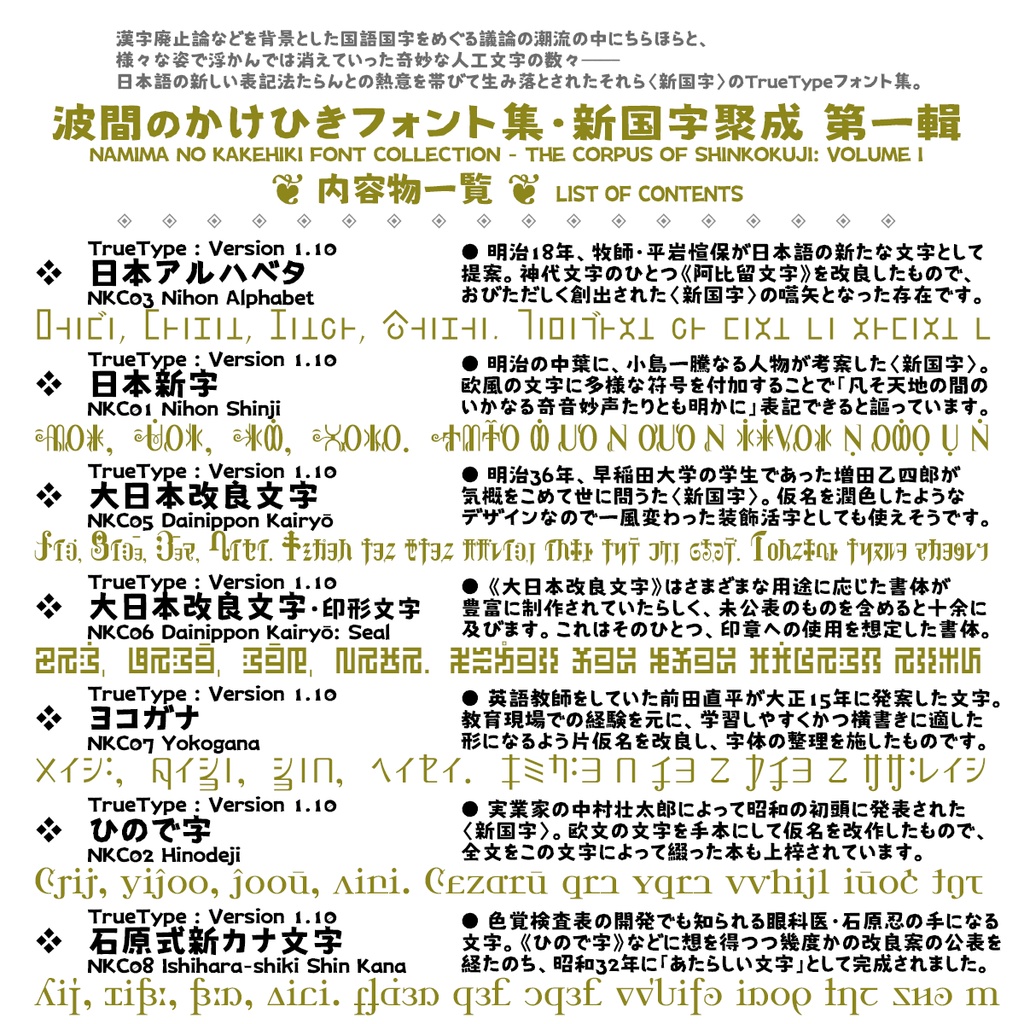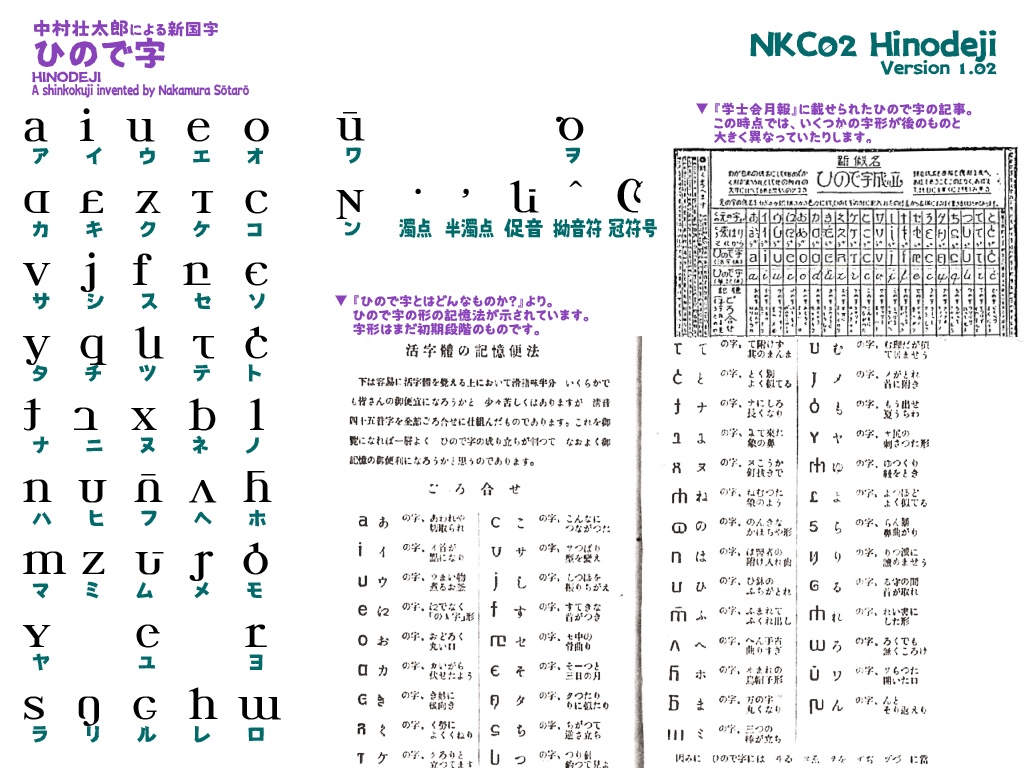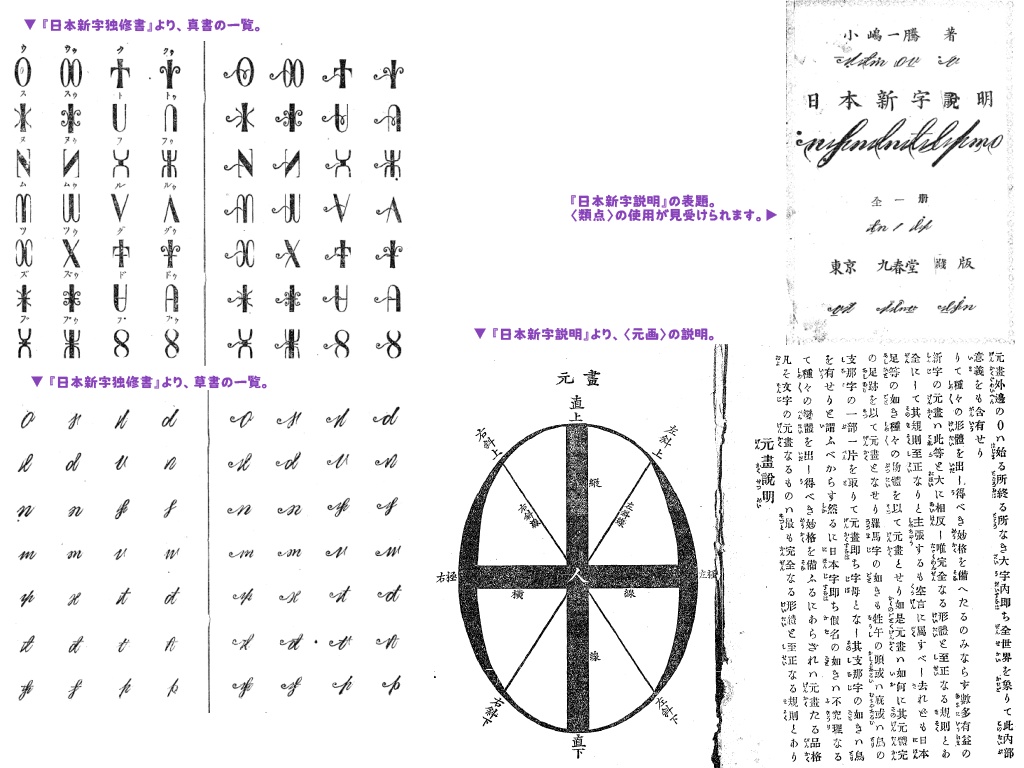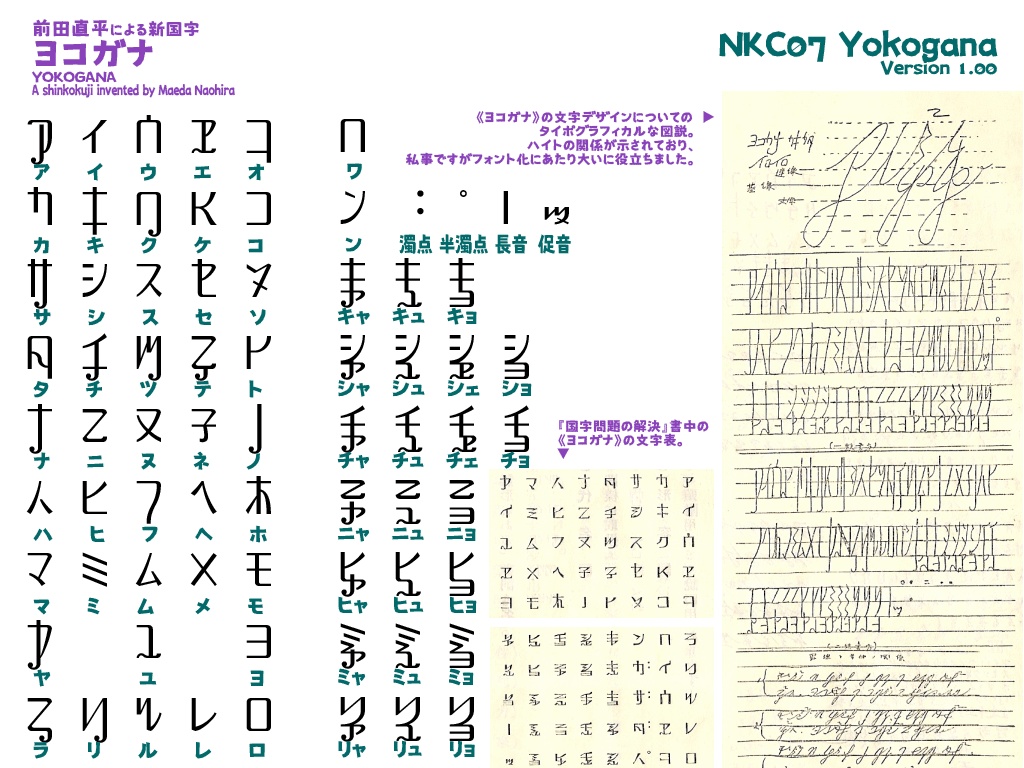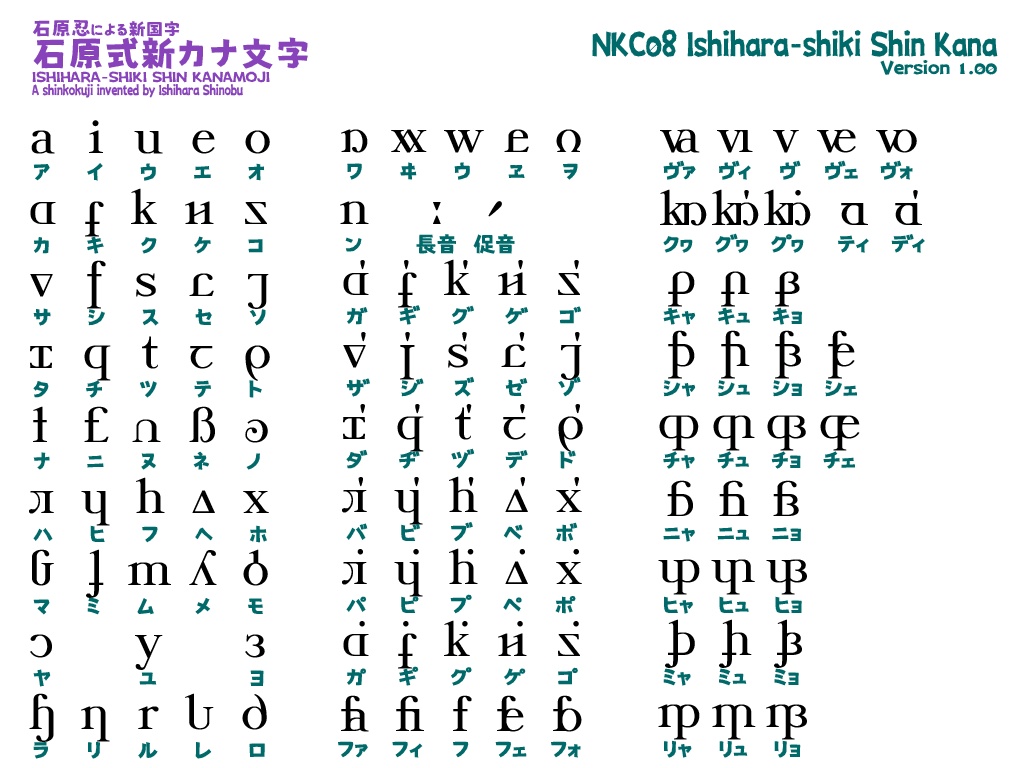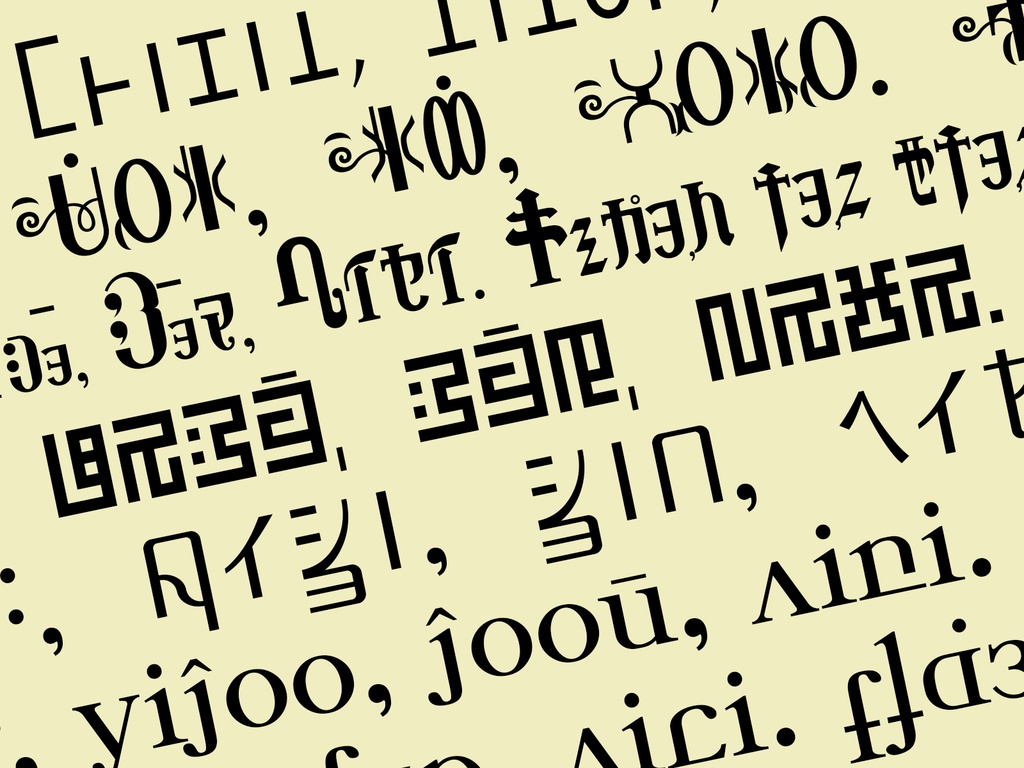
波間のかけひきフォント集・新国字聚成 第一輯
NAMIMA NO KAKEHIKI FONT COLLECTION - THE CORPUS OF SHINKOKUJI: VOLUME I 🔤 明治から昭和にかけて沸き起こった国語国字改革の熱情のなかで、仮名や漢字に代わる日本語の新しい表記法たらんとしてさまざまに生み出され、やがて歴史の波間に消えていった奇妙な人工文字群〈新国字〉のフォント集。 各々の文字の詳しい解説付き。 いずれもおおむね仮名に対応した文字なので、ちょっとした暗号文のようなものとして使ってもおもしろいと思います。 ❖ 当フォント群の一般的な目的での使用 (文書や画像の作成、装飾としての利用など) は私用、同人、商用を問わずご自由にどうぞ。 ✽ 形式: フォントはTrueType、添付資料はPDF
収録フォント群
❖「日本アルハベタ」 NKC03 Nihon Alphabet ❖「日本新字」 NKC01 Nihon Shinji ❖「大日本改良文字」 NKC05 Dainippon Kairyō ❖「大日本改良文字・印形文字」 NKC06 Dainippon Kairyō: Seal ❖「ヨコガナ」 NKC07 Yokogana ❖「ひので字」 NKC02 Hinodeji ❖「石原式新カナ文字」 NKC08 Ishihara-shiki Shin Kana